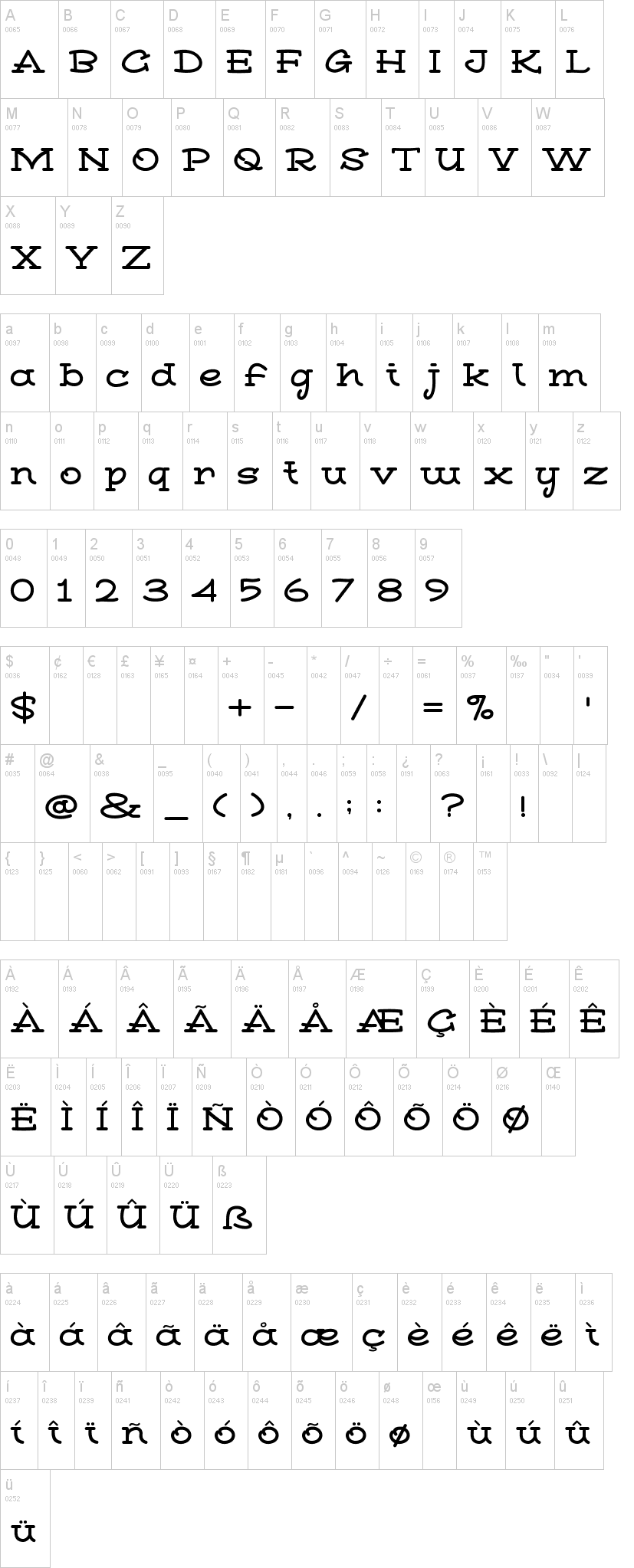
Vixen Deer
Vixen Deer 是一种免费的手写字体,由一位名叫 Lauren Thompson 的设计师创建。这个字体的风格非常独特,它融合了手写和印刷的元素,形成了一种有机而富有个性的外观。Vixen Deer 字体包括大写和小写字母、数字、标点符号和一些其他的特殊字符。这个字体适用于很多不同的设计项目,包括标志、海报、包装、明信片、T恤等等。如果你正在寻找一个充满活力、自然和独特的字体,那么 Vixen Deer 可能是一个很好的选择。
Vixen Deer是一款非常不错的手写艺术字体,具有很好的视觉感,适合于文化类的宣传设计、商业类品牌的广告和产品包装设计以及个性化文字排版等较多场景。
Vixen Deer字符映射图